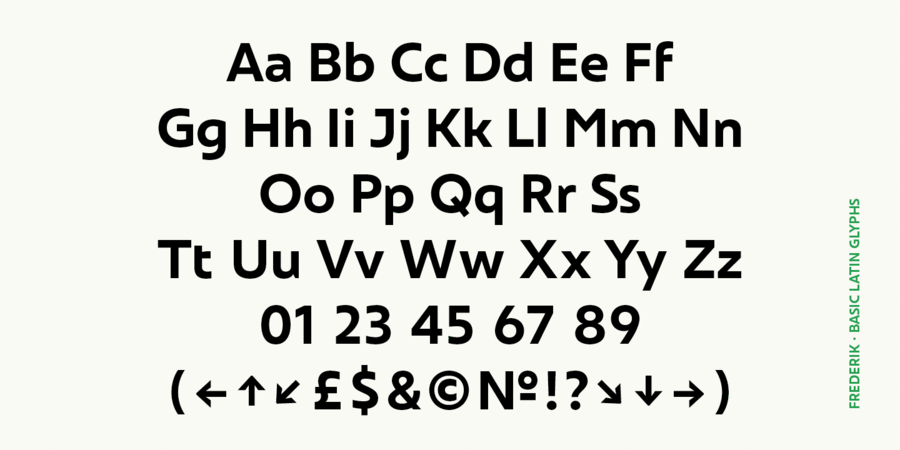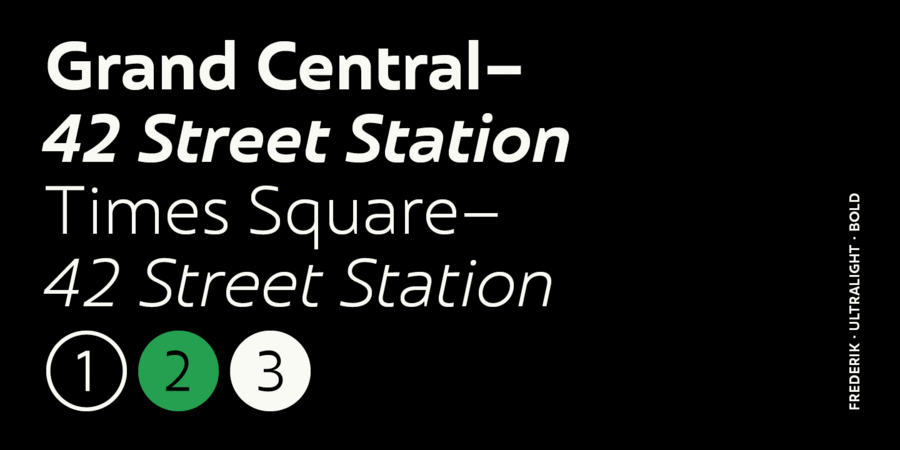
Традиційний гуманістичний гротеск у сучасній інтерпретації. Свіжий та нейтральний на вигляд, але водночас органічний та дружній. Frederik пропонує 10 накреслень від тонкого до чорного, а також відповідні курсиви. Звичайний і середня вага відмінно підходять для дрібного основного тексту, а Light і Heavy найкраще підходять для демонстраційних цілей, що робить Frederik універсальним шрифтовим сімейством для широкого застосування. Функції Opentype включають нижні й верхні індекси, дроби, цифри в колах, лігатури, численні стрілки, включно зі збільшеною довжиною, а також підтримку всіх латинських і кириличних мов. Frederik™ є торговою маркою компанії The Northern Block. Шрифт розробила Ксенія Білоброва у 2019 році.
Асоціації з сімейством шрифтів FrederikОсобистість і характер гарнітури:
мінімалістичний, делікатний, чистий, легкий, тонкий, сучасний, лаконічний, рівний, якісний, невагомий, точний, прозорий, дротяний, худий, динамічний, спокійний, ясний, чіткий, доступний, комфортний, Простий, глобалізований, глобалістічний, міський, формальний, зрозумілий, розумний, освічений, зручний, серйозний, інженерний, креслярський, діловий, твердий, мотивуючий, переконливий, міцний, надійний, стабільний, яскравий, важкий, сильний, впевнений, стійкий, потужний, помітний, активний, важливий, техногенний, тісний, суворий, амбітний
інновації, дієта, чистота, дизайн, прилад, гаджет, суспільство, Місто, одяг, коворкінг, наука, навігація, транспорт, аеропорт, метро, ліки, взуття, інженер, техніка, хімія, фізика, логістика, аптека, автобус, новини, політика, інструмент, енергетика, паливо, електростанція, технології, будівництво, машинобудування, завод, промисловість, верстат, тренажери Гарнітура має ознаки стилів: